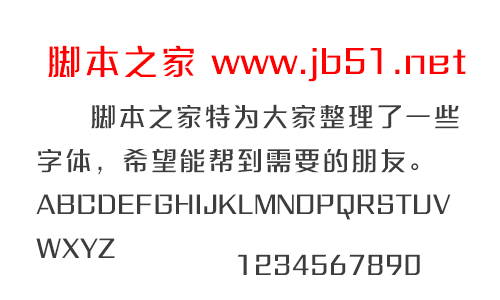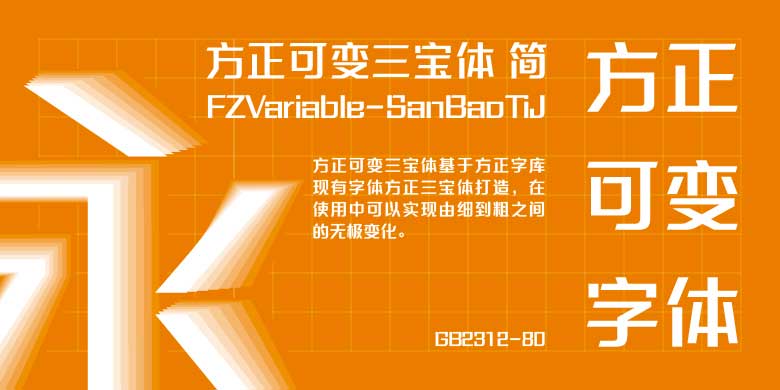
方正可變?nèi)龑汅w創(chuàng)意結(jié)合了流行的中文字體:綜藝體、剛黑體和聲寶體的精粹而成,這三款字體也是郭炳權(quán)老師的代表作,在中國、香港、澳門、臺灣、新加坡等都非常流行。三寶體包含了它們的特色和神韻,象征穩(wěn)重、創(chuàng)新、誠實、和諧,適合各行各業(yè)的宣傳,適合商業(yè)百搭。歡迎喜歡方正可變?nèi)龑汅w的朋友前來下載使用。
方正可變?nèi)龑汅w 支持文字粗細(xì)無級調(diào)節(jié),設(shè)計師通過調(diào)整字重軸(Weight)的變化,可以實現(xiàn)字形的平滑連續(xù)的細(xì)微調(diào)整,滿足不同版式的設(shè)計需求。